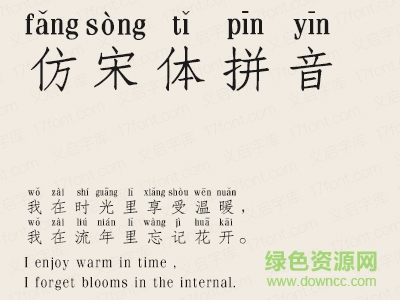
義啟仿宋體拼音版
義啟仿宋體拼音版是一款經(jīng)典的仿宋字體,拼音版在字體頭頂自帶拼音,方便廣大朋友學(xué)習(xí),實(shí)用性高,歡迎大家來(lái)綠色資源網(wǎng)下載使用!
義啟仿宋體拼音版,加了拼音的仿宋體,媽媽再也不用擔(dān)心寶寶不認(rèn)識(shí)字了。多音字以常用音調(diào)為準(zhǔn)。